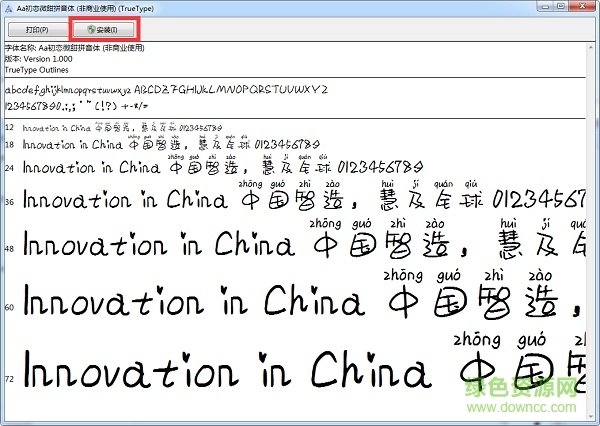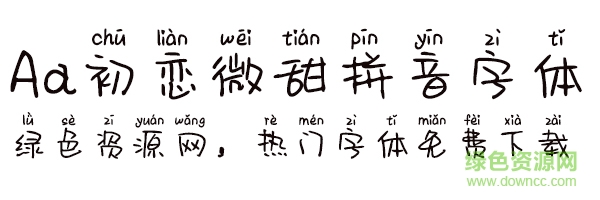
aa初戀微甜拼音字體
aa初戀微甜拼音字體是小編非常喜歡的一款字體,和大多數(shù)拼音字體一樣,擁有者規(guī)整不失靈氣的字體形狀。拼字加漢字的組合非常有創(chuàng)意!歡迎用戶來綠色資源網(wǎng)下載安裝。
字體介紹
aa初戀微甜拼音字體大小舒適,筆畫粗細(xì)均勻!視感較寬,彰顯個性;字形方正、整齊,辨識度高!常用來設(shè)計海報、平面排版等等。